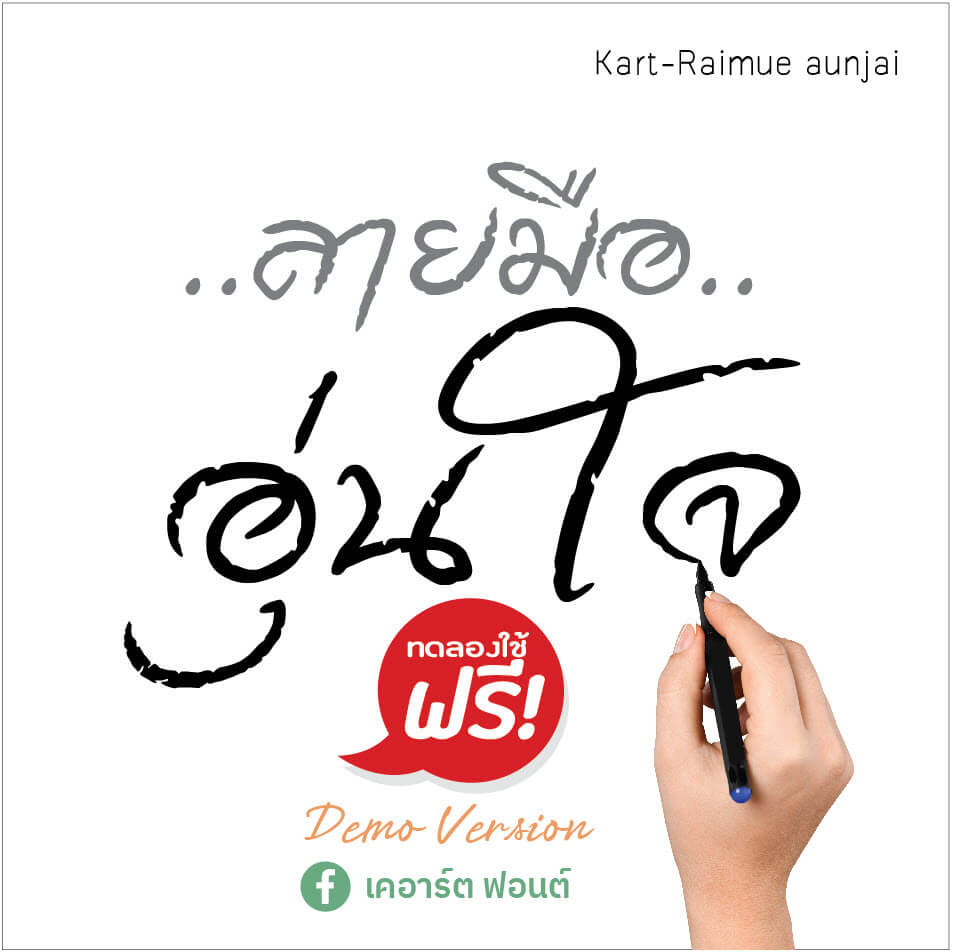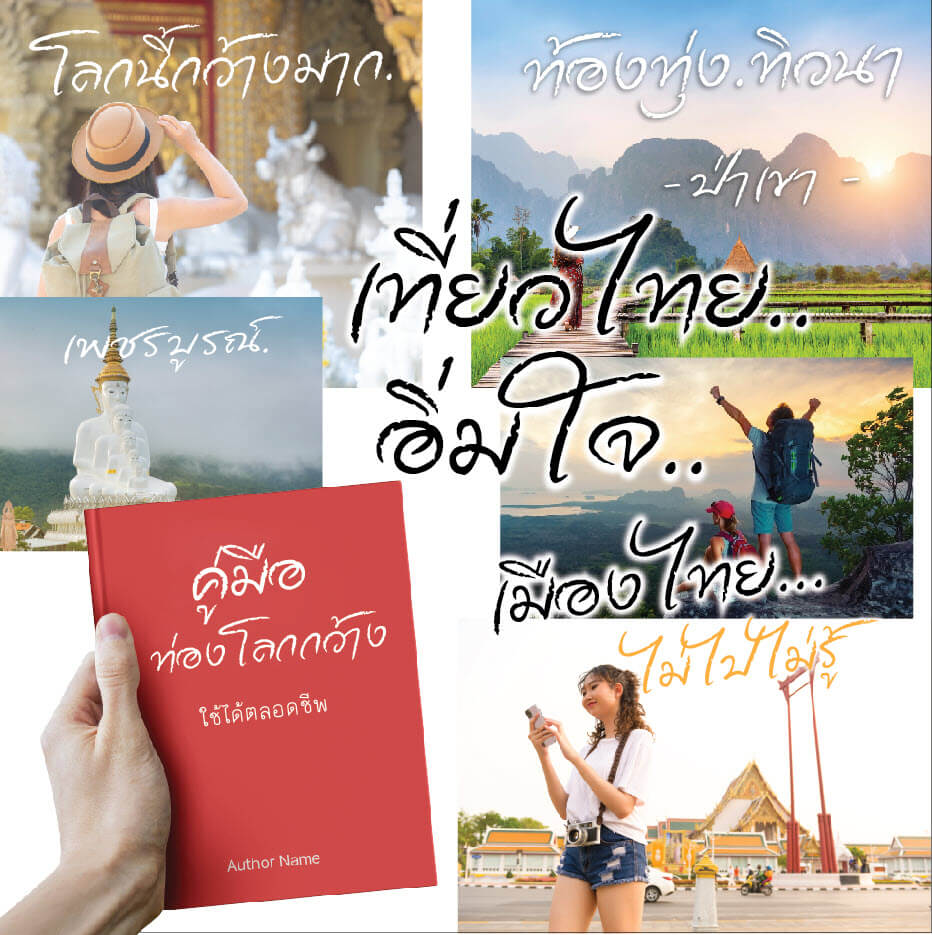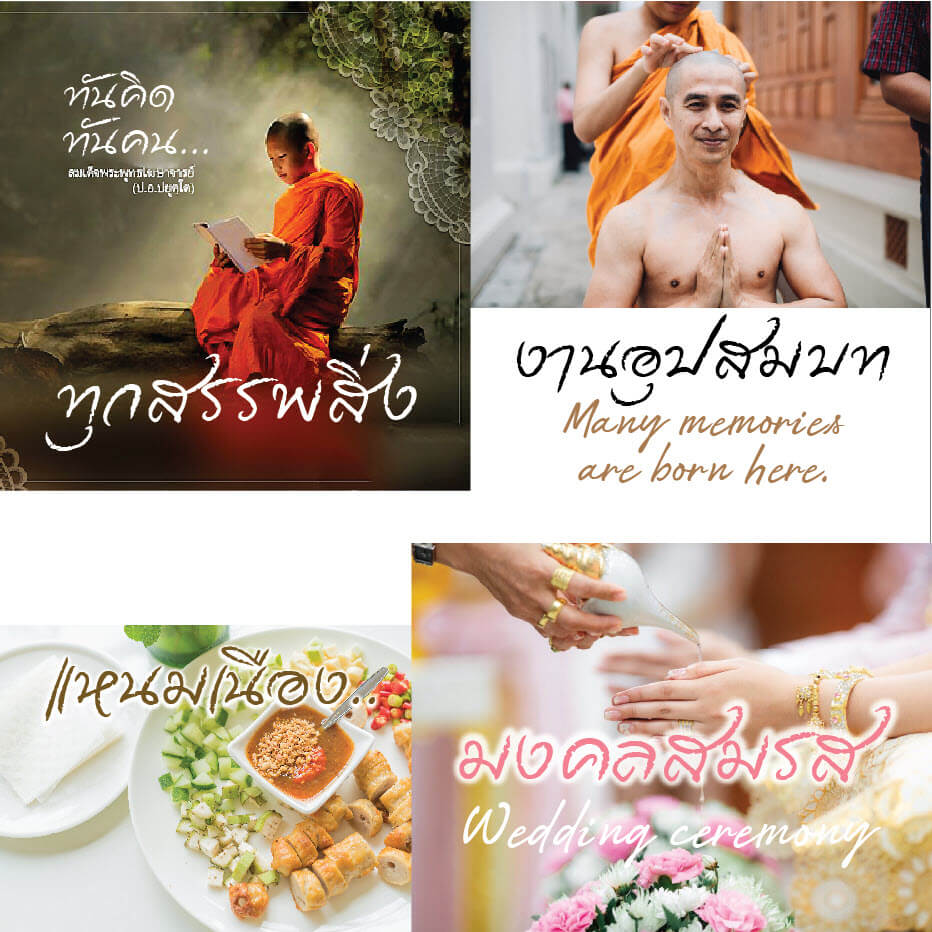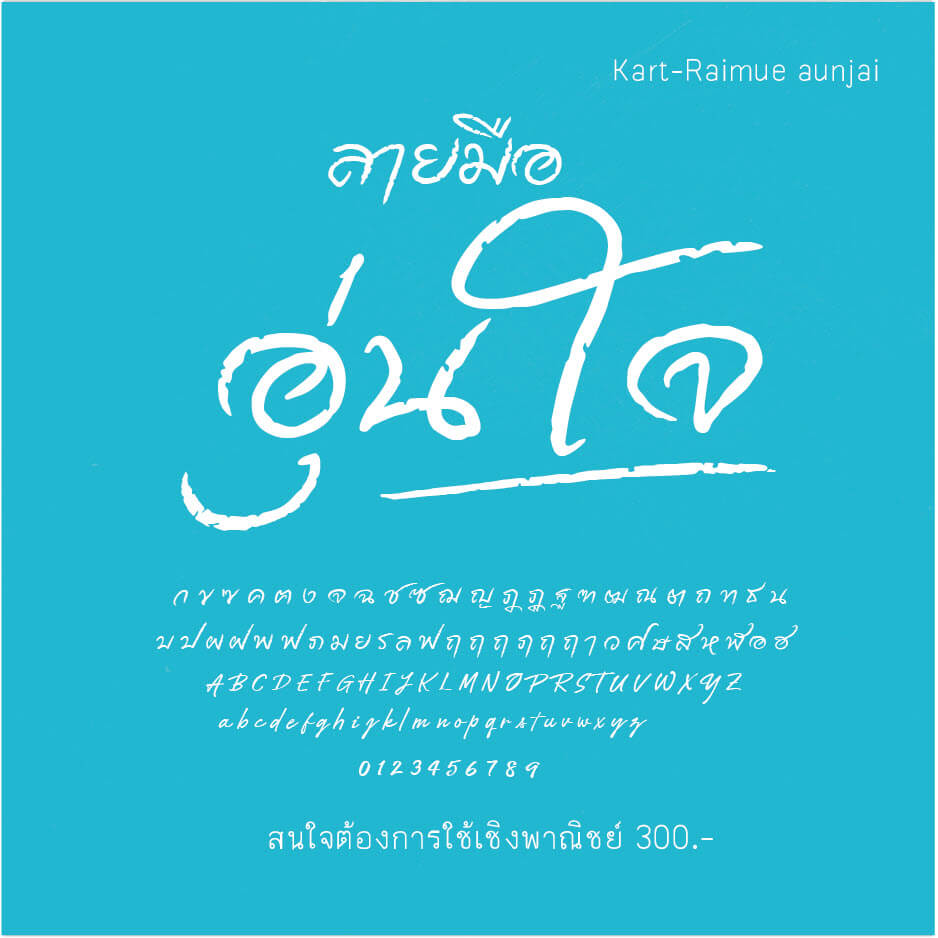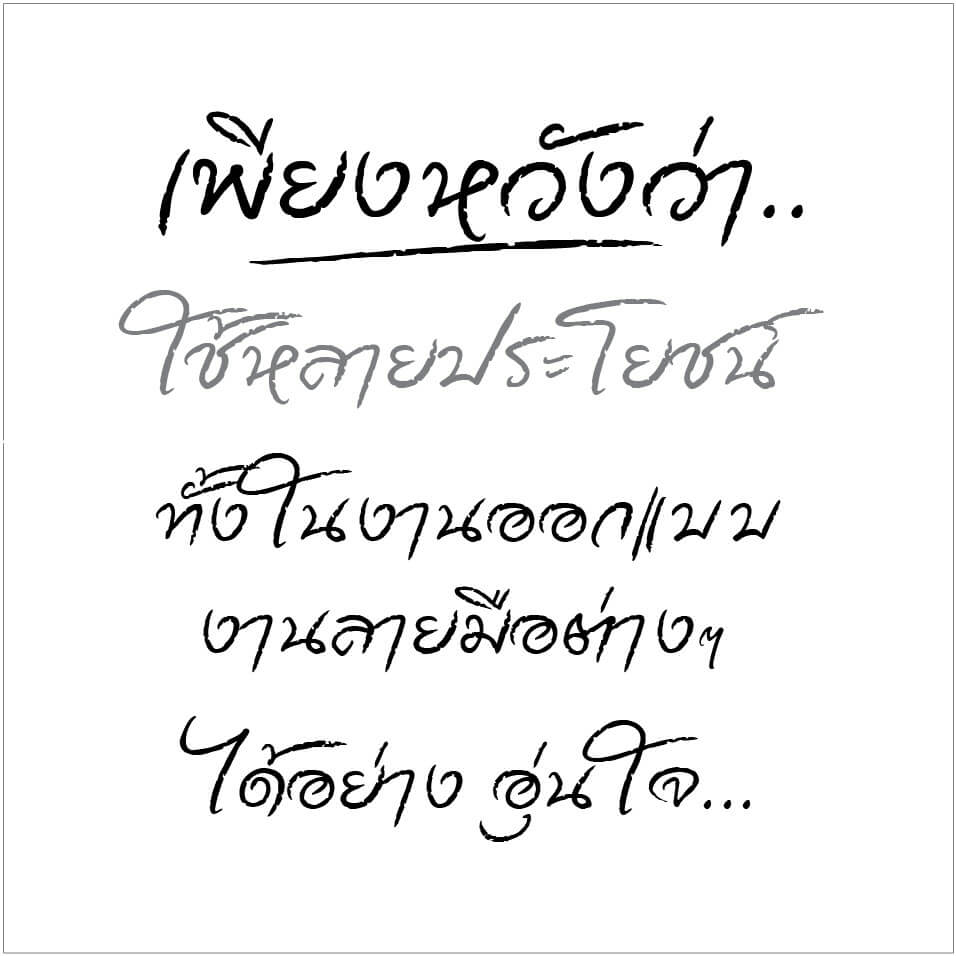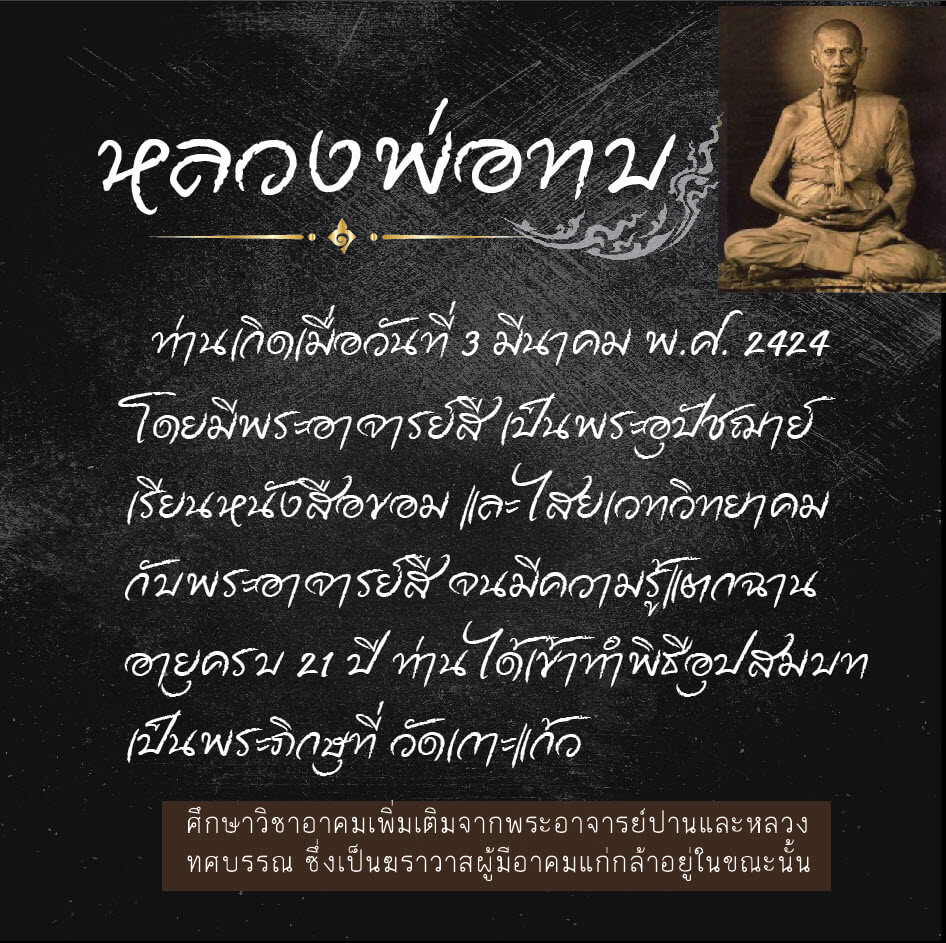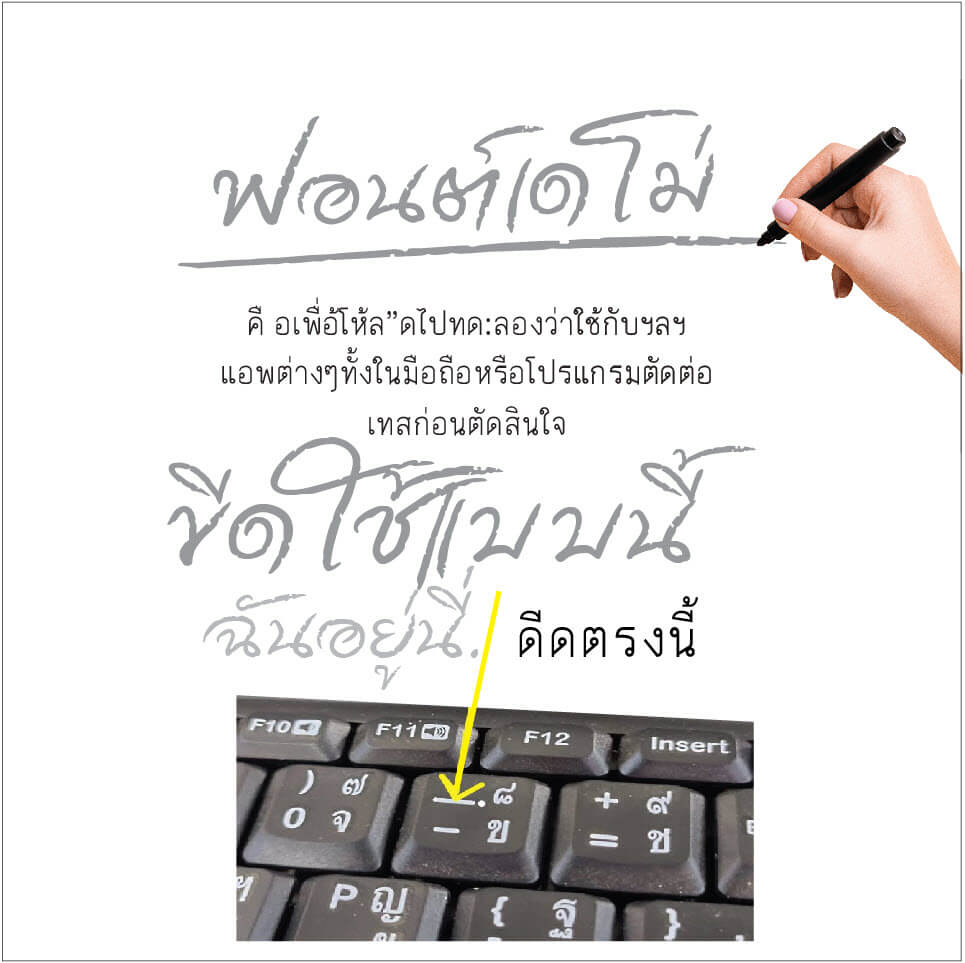
เคอาร์ต ลายมืออุ่นใจ (Kart-Raimue aunjai) เป็นฟอนต์ลายมือที่อยากให้มีกลิ่นชาร์โคลเน้นกลุ่มการใช้งานทั่วไป อยากให้ใช้ได้หลายประโยชน์
เคอาร์ต ลายมืออุ่นใจ (Kart-Raimue aunjai)